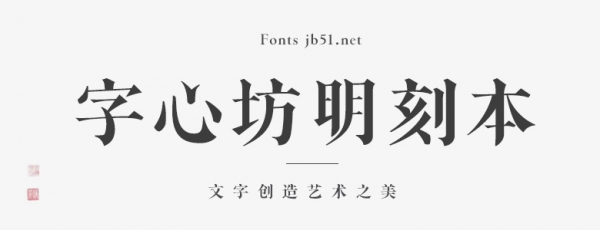
字心坊明刻本(古籍版)字形源于明代常熟文人毛晉創(chuàng)辦的汲古閣的刻印古籍善本。“凡汲古閣所抄本,散在人間者,無不精善”。秉承汲古閣古籍善本之字形特性,版刻刀法剔透,字形方正,端莊嚴(yán)謹(jǐn),古樸大方,起落頓筆有棱角。在飽有筆墨之意的同時,又突顯刀刻之鋒美,筆刀結(jié)合剛?cè)岵?jì)。
在秉承筆形間創(chuàng)新,結(jié)合當(dāng)代設(shè)計視覺環(huán)境,融入現(xiàn)代審美,適用場景更多元,筆畫造型清晰銳利,刪繁取簡,筆鋒凌厲,速度感強,粗細(xì)對比強烈,重現(xiàn)刀刻古韻之美。
一款歷經(jīng)六年復(fù)刻的字體,只為再現(xiàn)四百年前的匠心。
從2013年6月,至2019年8月,歷經(jīng)6年時間,共計7個設(shè)計師;
翻閱古籍幾萬余字,經(jīng)過近百個組樣稿的修改,最終確認(rèn)筆畫細(xì)節(jié)的定型設(shè)計;
歷經(jīng)5次整體重新設(shè)計和修正,共設(shè)計3萬余字樣,廢除近2萬余廢字字樣,最終定稿8000余字樣。